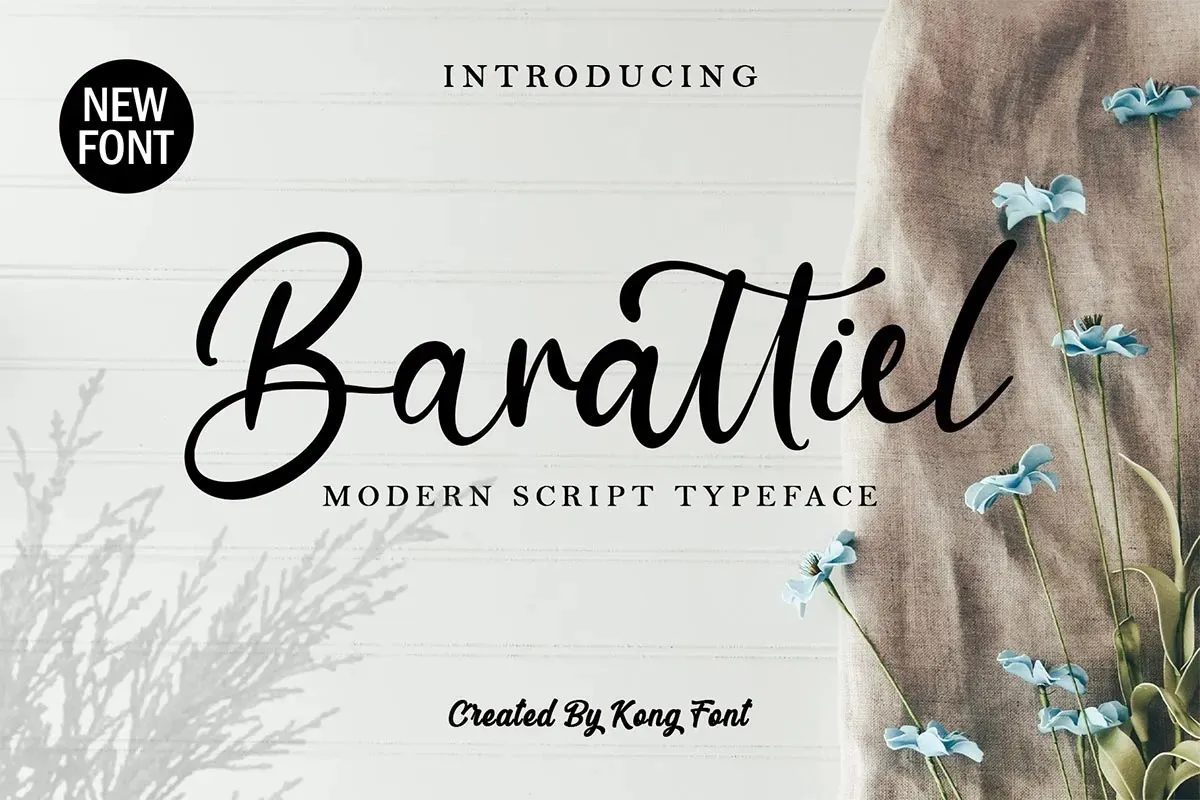
Barattiel Font
A Barattiel Font é uma elegante proposta para aqueles que valorizam a simplicidade e sofisticação na tipografia. Criada pelo designer Kong Font, essa fonte script apresenta caracteres finamente trabalhados, capazes de transformar qualquer texto em algo refinado, luxuoso e contemporâneo. Ideal para projetos onde uma delicadeza elegante se encaixa perfeitamente com um toque moderno, a Barattiel é perfeita para designers buscando incorporar nuances sutis ao seu trabalho gráfico. Seja para criar layouts arquitetônicos ou textos de propaganda em alta qualidade, esta fonte vai garantir que seus projetos possam ser vistos do mesmo modo que são sentidos – com classe e modernidade.